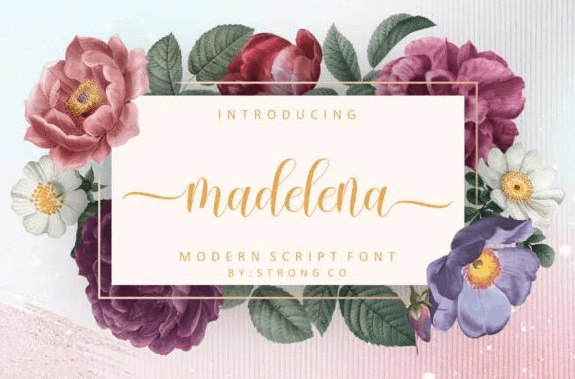
Madelena Font
Madelenais - это современный шрифт скрипта.
Стильная и женственная, Мадлена прекрасно смотрится в свадебных приглашениях, благодарственных открытках, цитатах, поздравительных открытках, логотипах, визитных карточках и многом другом.